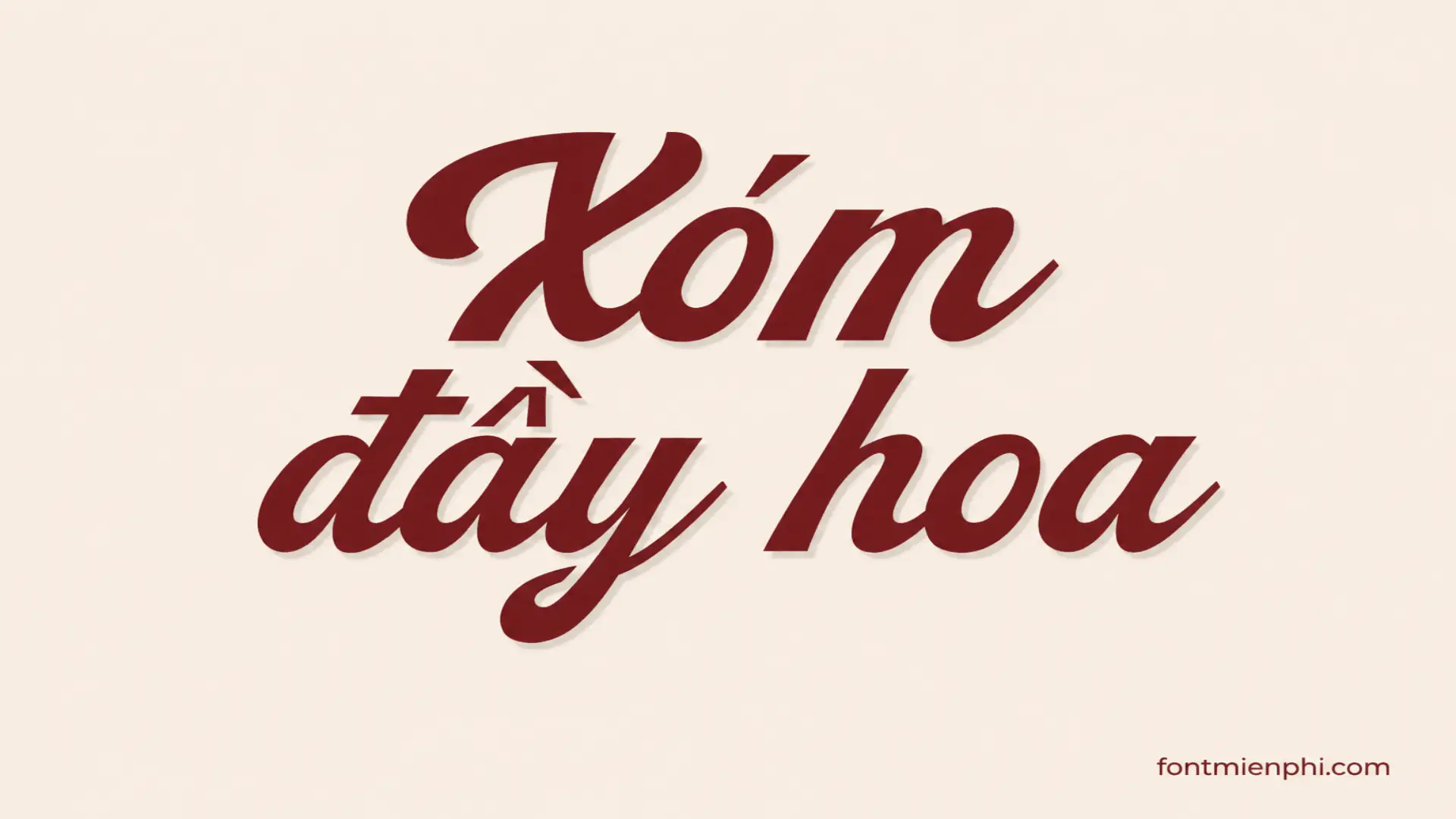
Font Việt hóa 1FTV VIP Peach Club
Tải Font Việt Hóa 1FTV VIP Peach Club – Phông Chữ Ngọt Ngào, Nữ Tính Và Đầy Cuốn Hút
Bạn đang tìm kiếm một phông chữ mang lại cảm giác tươi mới, ngọt ngào và tràn đầy sức sống cho các dự án thiết kế của mình? Font Việt hóa 1FTV VIP Peach Club chính là “chân ái” mà bạn không thể bỏ qua. Với phong cách trẻ trung, duyên dáng, bộ font này đang làm mưa làm gió trong cộng đồng Designer, đặc biệt là với những thiết kế hướng đến sự nữ tính và hiện đại.
1. Có gì đặc biệt ở Font 1FTV VIP Peach Club?
Đúng như tên gọi “Peach Club” (Câu lạc bộ quả đào), phông chữ này toát lên một vẻ đẹp ngọt ngào, mềm mại và vô cùng “nịnh mắt”.
1FTV VIP Peach Club là sự kết hợp hoàn hảo giữa những đường cong uyển chuyển và cấu trúc chữ hiện đại. Không quá cứng nhắc như các font Serif truyền thống, cũng không quá phá cách như các font Display hầm hố, Peach Club mang đến một nét thanh lịch, nhẹ nhàng nhưng vẫn đủ sức tạo điểm nhấn mạnh mẽ cho bất kỳ ấn phẩm nào.
Đặc biệt, phiên bản Việt hóa bởi 1FTV đã được đội ngũ xử lý vô cùng khéo léo. Các dấu câu tiếng Việt được tinh chỉnh tỉ mỉ, đặt đúng vị trí và hòa hợp tuyệt đối với đường nét gốc của bộ font, giúp bạn thoải mái sáng tạo mà không lo lỗi hiển thị.
2. Ưu điểm nổi bật của Font VIP Peach Club Việt Hóa
• Vẻ đẹp ngọt ngào, thanh lịch: Từng ký tự được uốn nắn tinh tế, tạo cảm giác thân thiện, dễ gần nhưng vẫn toát lên vẻ sang trọng.
• Hỗ trợ tiếng Việt hoàn hảo: Gõ tiếng Việt có dấu cực kỳ mượt mà, kerning (khoảng cách chữ) chuẩn xác, tối ưu hóa trải nghiệm đọc.
• Tính linh hoạt cao: Hoạt động tốt trên cả các bản in ấn sắc nét lẫn thiết kế Digital (Banner, Thumbnail, UI/UX).
3. Ứng dụng của Font Peach Club trong thiết kế đồ họa
Với sắc thái nữ tính và tươi mới, Font Việt hóa 1FTV VIP Peach Club là sự lựa chọn số 1 cho các lĩnh vực sau:
💄 Mỹ phẩm, Làm đẹp & Spa
Nét chữ mềm mại của Peach Club cực kỳ phù hợp để làm Logo, bao bì sản phẩm, catalogue hay các bài post mạng xã hội cho các thương hiệu mỹ phẩm, tiệm nail, spa và thời trang nữ.
🍰 Lĩnh vực F&B (Trà sữa, Tiệm bánh ngọt)
Nếu bạn đang thiết kế menu, biển hiệu hay sticker cho một tiệm bánh ngọt, quán trà sữa, hay quán cafe phong cách “bánh bèo”, phông chữ này sẽ giúp kích thích thị giác và tạo cảm giác ngon miệng, dễ thương ngay từ cái nhìn đầu tiên.
🎀 Thiệp cưới & Sự kiện lãng mạn
Sự thanh lịch của Peach Club biến nó thành một Typography tuyệt vời để thiết kế thiệp cưới (Wedding Invitation), thiệp chúc mừng 8/3, 20/10 hoặc các ấn phẩm mang chủ đề tình yêu, lãng mạn.